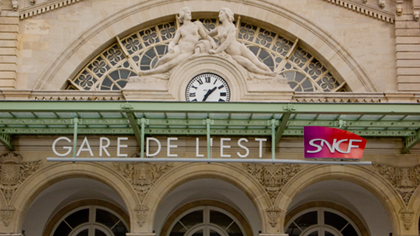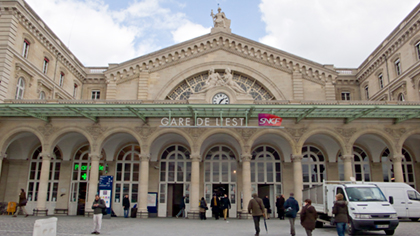
SNCF, le logo en situation sur un immeuble haussmannien
Vous vous souvenez certainement d’un des premiers billets de design et typo, SNCF, un logo dyslexique, je voudrais juste revenir quelques instants sur la déclinaison du logo qui pour moi confirme les doutes que j’avais émises il y a deux ans et demi.
Jetez un coup d’œil sur les deux photographies ci-dessous. La première est prise au niveau de la grille d’entrée de la Gare de l’Est, la seconde, aussi mais avec un coup de zoom optique. Qu’est ce que l’on constate?
Le manque de lisibilité “à distance” de la marque SNCF…
Comparez, le bloc marque rouge-mauve, à l’écriture en capitales de “LA GARE DE L’EST”. L’interlettrage de ces lettres composées dans une “Europe” (Futura) est mille fois plus propice à la lecture que les quatre lettres resserrées du sigle SNCF. Tous les graphistes savent cela. Ça fait même partie des bonnes pratiques en typographie de signalisation que de soigner les approches afin de garder un max. de lisibilité.
Alors que reste-t-il de ce bloc marque, un “misérable” cartouche à la forme imprécise —vue de loin— mais dont les couleurs attirent l’œil au premier regard. “Dites une couleur et un outil…” 90% pour cent des gens répondent rouge et marteau. Effectivement, pourquoi s’en faire.
Pour le logo de la Société Générale la réflexion sur la couleur relevait à peu près du même niveau. Comme pour le rond rouge de la marque ELF au début des années 70. Désolé, on est loin de la qualité de création et de réflexion que méritait cette grande Société Nationale des Chemins de Fer. Mais qui se souvient d’ailleurs du “Nationale” et des Chemins de Fer, à l’heure où le TGV va presque aussi vite que les lignes intérieurs de l’aviation civile?
La question qui me semble essentielle dans ce débat:
Cette marque ne semble pas en être une. Ce bloc-marque ressemble plus à un packaging d’une tablette de chocolat. Il s’agit plus d’une illustration alimentaire que de la représentation d’une entreprise de service de taille industrielle. Les signifiants sont bavards (par la richesse des couleurs) et anecdotiques (la forme du cartouche) et l’on ne voit pas comment on peut l’intégrer dans une stratégie marque-archi-print-web.
Bien sûr qu’il fonctionne sur le site web. On a presque le sentiment qu’il (le bloc-marque) a été conçu pour cela. De même il fonctionnera en Print lorsqu’il s’agira de signer une annonce ou un document. Les yeux à 25cm de la marque… certes. Mais lorsque vous êtes devant un immeuble haussmannien qui devrait porter l’empreinte du prestige de la SNCF, on se retrouve avec la sale impression d’une pièce rapportée à la hâte, style PLV d’une marque alimentaire, en tête de gondole.
Voilà, je peux me tromper. On peut toujours se tromper. On analyse avec ses codes personnels, ses goûts et sa sensibilité…
Je profite d’un moment de répit pour revenir sur le logo de la SNCF. Je crois que ce qui nous dérange dans ce logo ce n’est pas tant sa forme en elle-même que la manière incohérente dont celle-ci entend signifier le dynamisme. Incohérente parce que contradictoire. En effet, par sa forme générale, issue du TGV, le cartouche dans lequel s’inscrit le nom de la société semble vouloir nous parler le langage de l’aérodynamique. La courbe qui décline vers la droite signifie que nous sommes à l’avant du train et que ce train se déplace de gauche à droite, autrement dit qu’il va dans le sens de l’écriture. La même forme tournée dans l’autre sens nous aurait donné l’impression non pas d’un départ mais d’un retour, ce qui aurait été rassurant, peut-être, mais un peu contrariant aussi et en tout cas pas très dynamique.
L’ennui, pour les concepteurs du logo, c’est qu’une courbe aérodynamique qui fend l’air en se déplaçant vers la droite doit forcément être inclinée dans l’autre sens, ce qui a pour conséquence que, pour être lue comme se déplaçant vers la droite et donner l’impression d’aller de l’avant, la forme générale du logo doit tendre vers la gauche, dans le sens opposé à celui de l’écriture. La courbe qui en résulte, lue de gauche à droite, est une courbe descendante, donc négative (à nos yeux), le genre de courbe qu’aucune société au monde ne souhaite montrer à ses actionnaires.
Il faut dire que, d’une manière générale, l’inclinaison vers la gauche est généralement perçue comme étant rétrograde: pour les graphologues amateurs que nous sommes tous sans le savoir, une écriture inclinée vers la gauche trahit un attachement au passé, elle est un signe d’inquiétude face à l’avenir, pour ne pas dire d’inhibition. Notre écriture nous ressemble, elle est à notre image, par un effet mimétique facile à comprendre: quand nous marchons vite ou que nous courons, notre corps est projeté vers l’avant et nous nous inclinons naturellement dans le sens de la marche. Ainsi en est-il de notre écriture: la cursive s’incline dans le sens de la course, et l’italique, qui en est issue, est elle aussi inclinée dans le sens de la lecture, c’est-à-dire, dans le cas de l’écriture latine, vers la droite.
On voit tout de suite que ces deux dynamismes sont contradictoires. Celui de notre écriture, comme celui du corps humain, exige que la forme penche à droite. Les lois de l’aérodynamique réclament au contraire que, pour opposer une moindre résistance à l’air, la forme d’un véhicule s’incline dans le sens contraire à celui de la marche, qu’il s’agisse du fuselage d’un avion ou de l’avant du TGV. Partagés entre la logique aérodynamique et la logique mimétique, ceux qui ont dessiné ce logo, ou ceux qui l’ont choisi, ont tenté de ménager la chèvre et le chou: ils ont commencé par suggérer la courbe caractéristique de l’avant du TGV, puis, au lieu de laisser cette courbe finir naturellement en pointe en bas à droite, ils l’ont arrêtée net selon un angle de 18° qui semble faire la moyenne des différents angles des quatre lettres en italique (entre 12° et 30°) — un angle qui est peut-être celui d’un homme qui marche à grands pas ou qui court, mais qui ralentirait beaucoup les trains si on les construisait suivant ce modèle.
Il aurait fallu choisir l’une ou l’autre de ces deux logiques et s’y tenir. Les deux langages sont incompatibles, et à trop vouloir les ménager on finit par contrarier tout le monde sans parvenir à satisfaire personne.